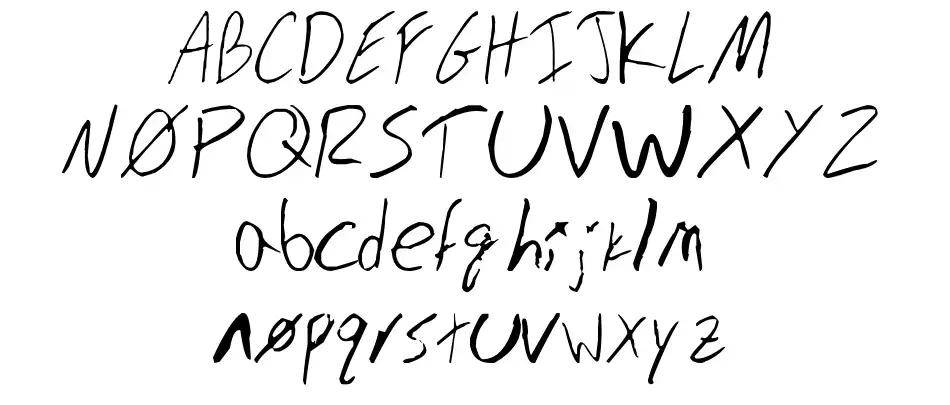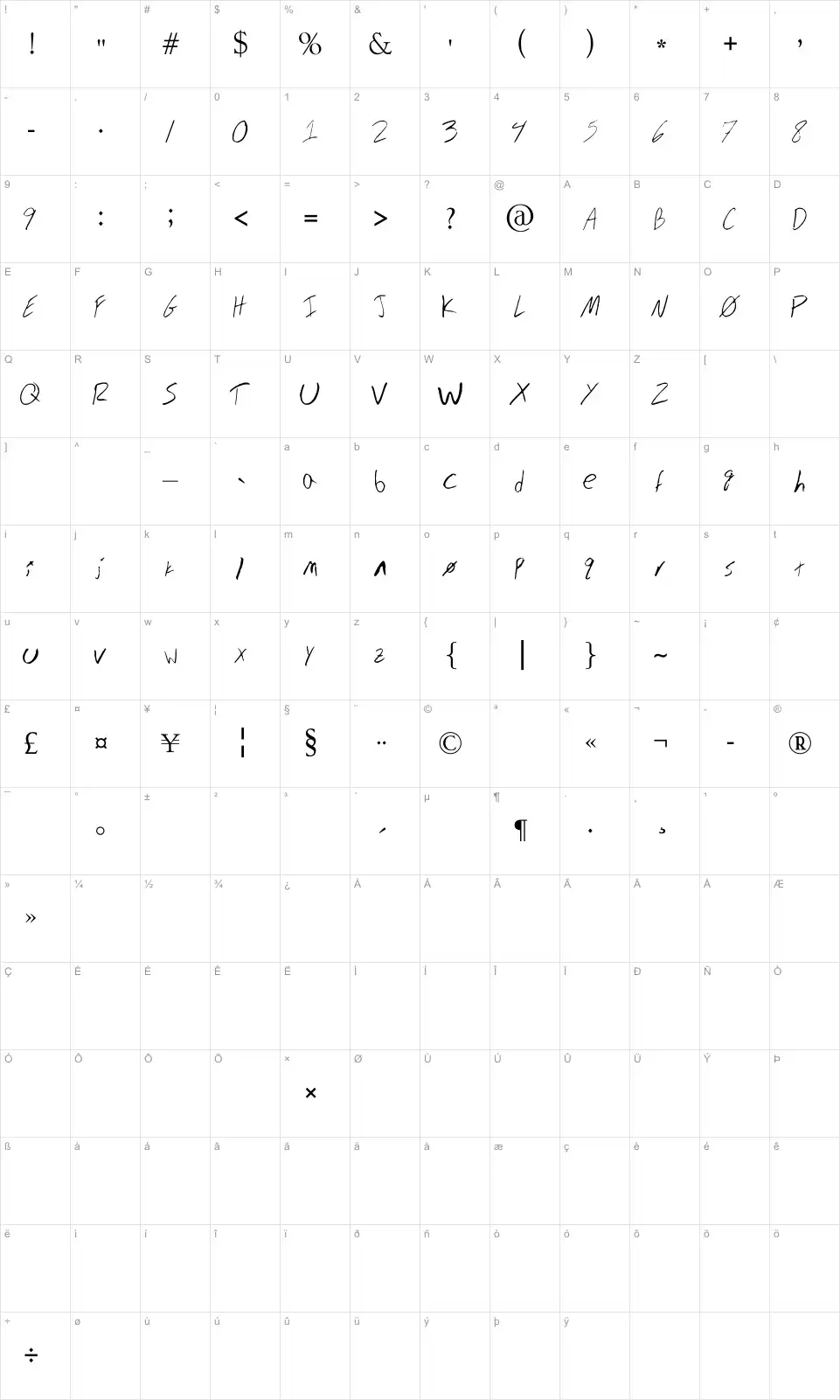
Desculpe pela confusão, mas parece que há um mal-entendido. A descrição solicitada está relacionada à fonte Typical Guy Font, mas a descrição fornecida inclui informações sobre uma fonte chamada “Looking for the Typical Guy Font”. A fonte mencionada na descrição original é realmente uma fonte Script de Carlos Perez. Entendo que você precisa criar uma descrição em português para essa fonte em uma categoria de script, com foco em recursos gráficos e em uma linguagem informativa e convidativa. Aqui está uma tentativa de criar essa descrição: A Typical Guy Font, criada por Carlos Perez, é uma excelente opção para qualquer designer em busca de uma fonte Script de qualidade. Com um estilo despojado e natural, essa fonte é ideal para criar textos de e-mail, blogs ou até mesmo para o design gráfico de projetos pessoais. Com seu formato TTF, é perfeitamente compatível com todos os sistemas operacionais modernos. Se você está procurando por uma fonte que seja mais natural e despojada, a Typical Guy Font é uma excelente escolha. Seu formato de texto personalizado permite que você veja como a fonte ficará antes de usá-la, dando-lhe total controle sobre seu design. Com 14KB de tamanho, a fonte é fácil de baixar e instalá-la em seu computador. A fonte está disponível gratuitamente para uso pessoal, sem necessidade de licença adicional. É perfeita para qualquer projeto que exija uma fonte Script elegante e despojada. Seja para um projeto pessoal ou profissional, a Typical Guy Font é uma opção ótima para adicionar um toque único e natural ao seu design.
Categoria: Script › Handwritten
Designer: Carlos Perez